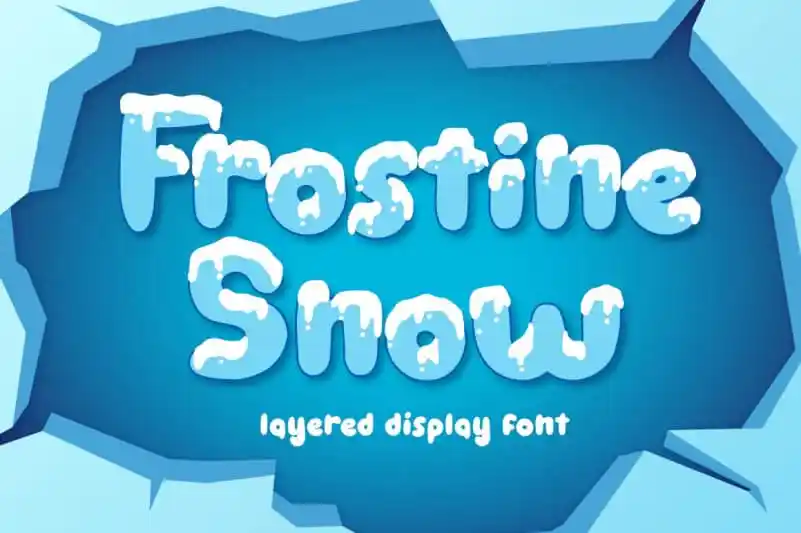
Frostine Snow Display Font – Fonte Grátis
Frostine Snow Display Font
A Frostine Snow Display Font é uma tipografia extensa e bold repleta de personalidade. Perfeita para criar imagens animadas para o Natal, especialmente cardes de natal. Esta fonte pode ser usada sozinha ou com a versão sobrecarregada colocada acima para um efeito neve-cabecuda. Ela é uma escolha ideal para tornar suas mensagens de Natal ainda mais festivas. Além disso, é super fácil de usar para criar efeitos 3D usando Frostine Snow fonte. Quando você combina esta fonte com outras, o resultado pode ser realmente surpreendente! Ideal tanto para designers profissionais quanto aqueles que iniciam no universo da design gráfica. É uma excelente opção para criar um visual único e atraente para qualquer projeto de design.